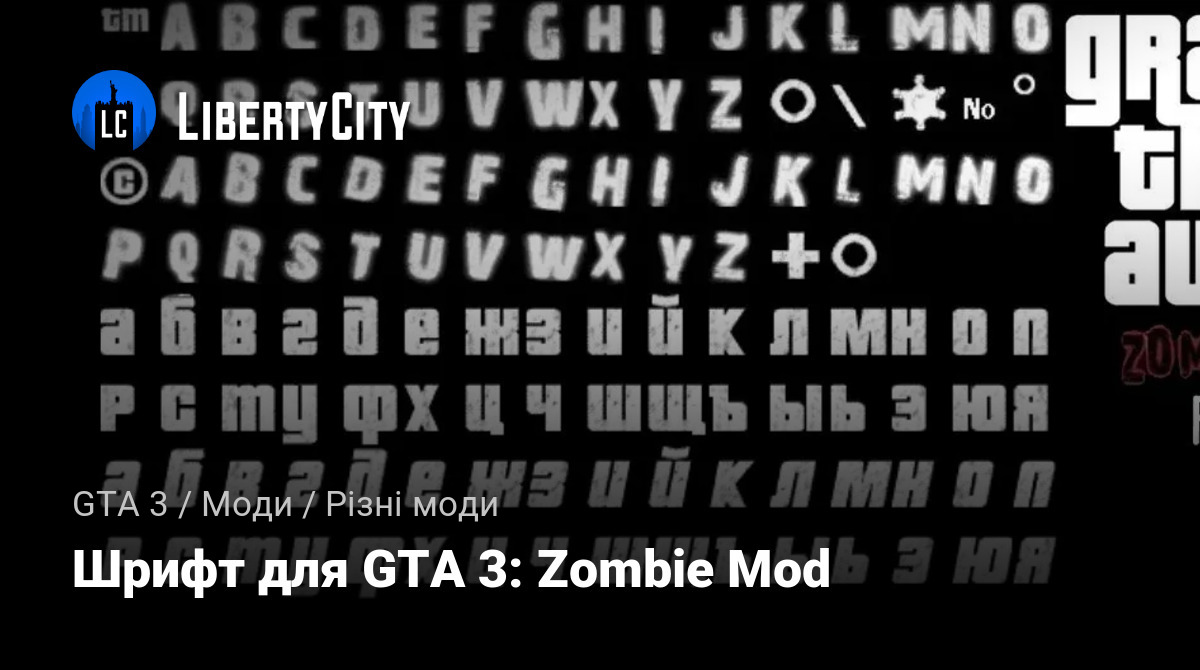
Шрифт для GTA 3: Zombie Mod
Шрифт для GTA 3: Zombie Mod.
Шрифт з GTA: Raccoon City Stories, перенесений в GTA 3: Zombie Mod.
Шрифт був адаптований під шрифт оригінальної GTA 3.
У тому моді були знаки оклику після деяких букв, а також злиті літери - я намагався це виправити, але можуть бути й інші дрібні та незначні помилки, які виправити не зміг. Також ще одна особливість - перефарбовані написи на зразок назв автомобілів і назв районів міста пишуться оригінальним шрифтом. Таке рішення було прийнято через те, що другий файл зі шрифтами у мене чомусь не хоче замінюватися, а там якраз і знаходяться ці шрифти.
Шрифт для GTA 3: Zombie Mod.
Шрифт из GTA: Raccoon City Stories, перенесённый в GTA 3: Zombie Mod.
Шрифт был подогнан под шрифт оригинальной GTA 3.
В том моде были восклицательные знаки после некоторых букв, а также сливающиеся буквы - это всё я постарался исправить, но могут быть и другие мелкие и незначительные косяки, которые исправить не смог. Также ещё одна фишка - перекрашенные надписи по типу названий машин и названий районов города пишутся оригинальным шрифтом. Такое решение было принято из-за того, что второй файл со шрифтами у меня почему-то не хочет заменяться, а там как раз-таки находятся эти шрифты.